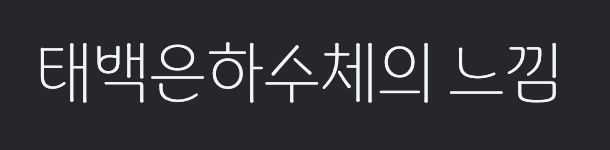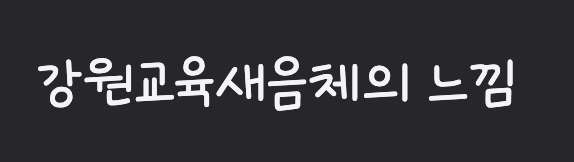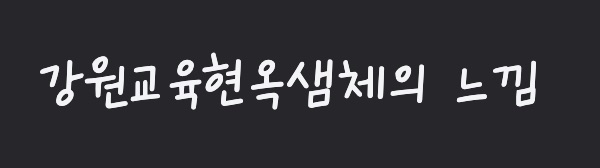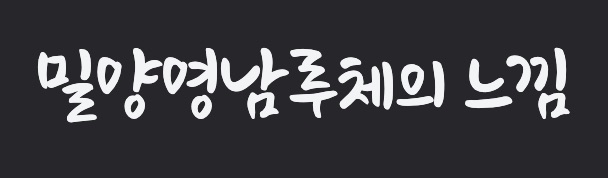
개인적인 용도로 사용하든, 상업적인 목적이든 폰트에 따라 디자인의 느낌이 달라지기 때문에 많은 분들이 좋은 폰트를 찾고자 많은 노력을 하시는데요. 오늘은 정말 많은 폰트 중에 폰트 제작자 허가 없이 누구나 상업용으로 마음껏 사용가능한 총 9종의 폰트를 소개하려고 합니다.
태백 은하수체
태백시에서 만든 폰트입니다. 태백은 평균 해발고도가 900m라고 합니다. 하늘과 가까운 도시인데요. 청명한 하늘에 반짝이는 은하수를 모티브로 만들었다고 하네요. 그래서 그런지 폰트도 산뜻합니다.
강원도교육청 무료서체 5종
강원도 교육청에서 배포한 서체인데요. 총 4종류의 서체를 배포했습니다. 각 폰트의 느낌을 보시겠습니다.
강원교육모두체
강원교육튼튼체
강원교육현옥샘체
강원교육새음체
밀양아리랑 서체 4종
밀양아리랑이라는 전통적인 요소를 모티브로 만들어진 서체입니다. 밀양시민의 서체를 폰트화 했다고 하네요.
뭔가 붓글씨나 캘리그라피 느낌이 필요할 때 사용하시면 좋을 것 같습니다.
밀양아리랑체
밀양영남루체
밀양해맑은상상체
밀양아리랑고딕체